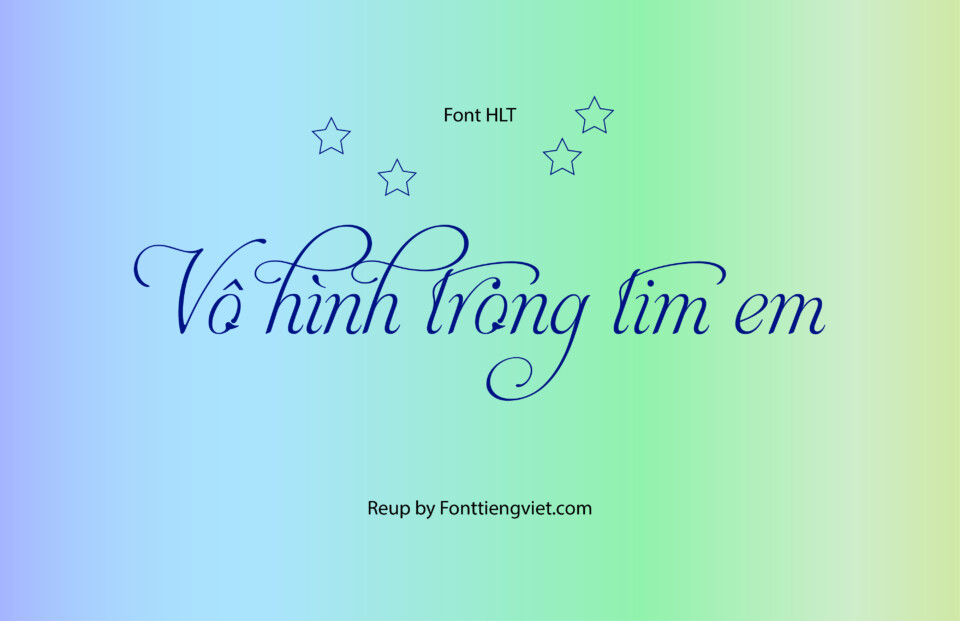
Font Việt hóa HLT AphroditeSlimStylistic
Tải Font Việt hóa HLT AphroditeSlimStylistic Miễn Phí Cho Thiết Kế Sang Trọng
Giới thiệu về Font Việt hóa HLT AphroditeSlimStylistic
Trong thế giới đồ họa, việc lựa chọn một Font Miễn Phí chất lượng luôn là ưu tiên hàng đầu của các nhà thiết kế. Font Việt hóa HLT AphroditeSlimStylistic nổi lên như một biểu tượng của sự thanh lịch và tinh tế. Đây là bộ font chữ thuộc phong cách Calligraphy hiện đại, được chau chuốt tỉ mỉ với những đường nét uốn lượn mềm mại. Phiên bản Việt hóa này giúp người dùng dễ dàng sử dụng trong các phần mềm thiết kế mà không lo lỗi font, đặc biệt phù hợp cho các văn bản tiếng Việt cần sự sang trọng.
Đặc điểm nổi bật của Font Việt hóa HLT AphroditeSlimStylistic
Nét chữ nghệ thuật và tính ứng dụng cao
Font Việt hóa HLT AphroditeSlimStylistic sở hữu hệ thống ký tự thay thế phong phú, cho phép người dùng sáng tạo không giới hạn. Các đường nét mảnh mai nhưng sắc sảo tạo nên cảm giác bay bổng, rất thích hợp cho các thiệp mời đám cưới, bìa sách nghệ thuật hoặc các thiết kế thương hiệu cao cấp. Sự kết hợp giữa cổ điển và hiện đại giúp bộ font này không bao giờ lỗi mốt trong mắt các chuyên gia đồ họa.